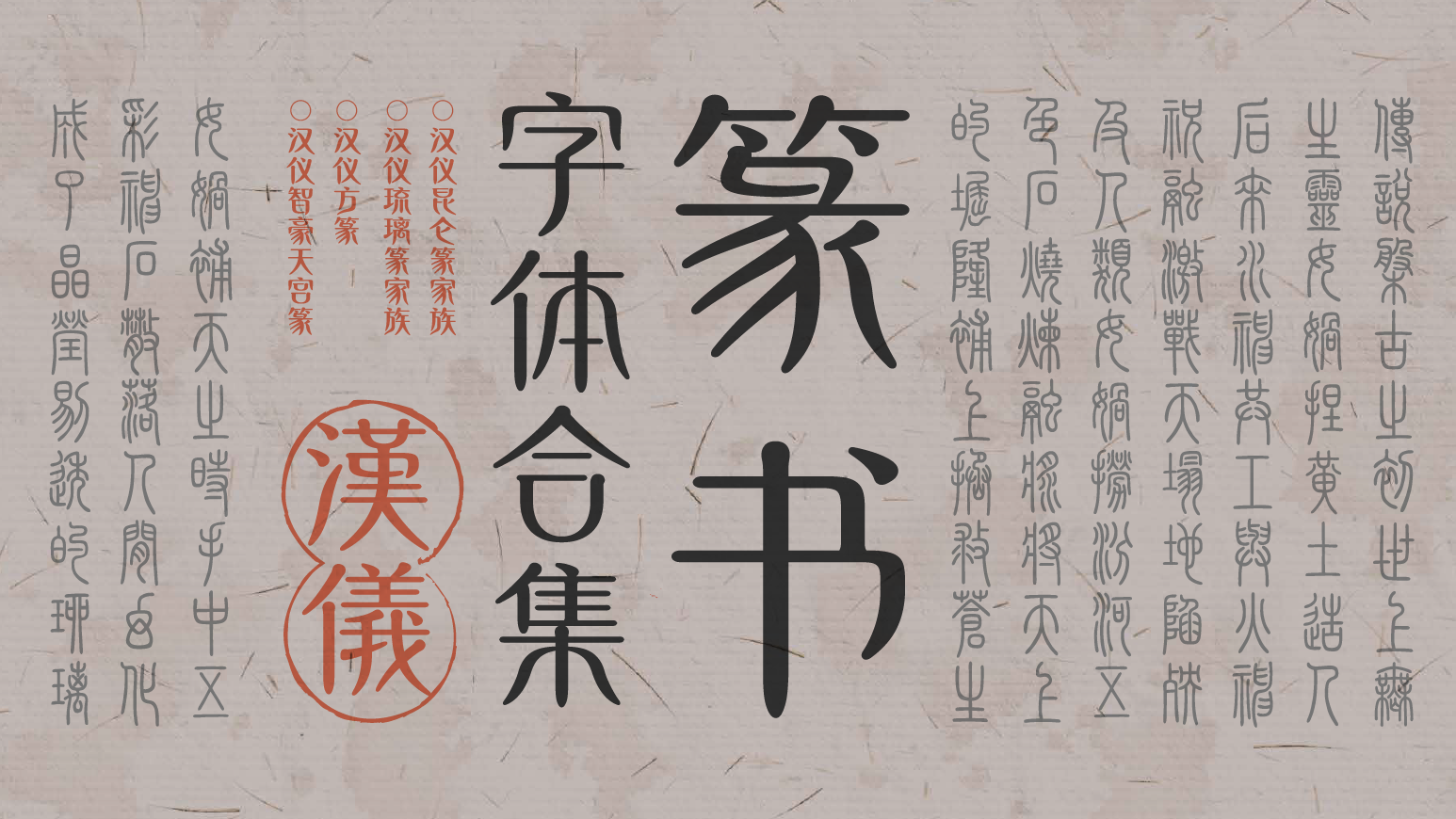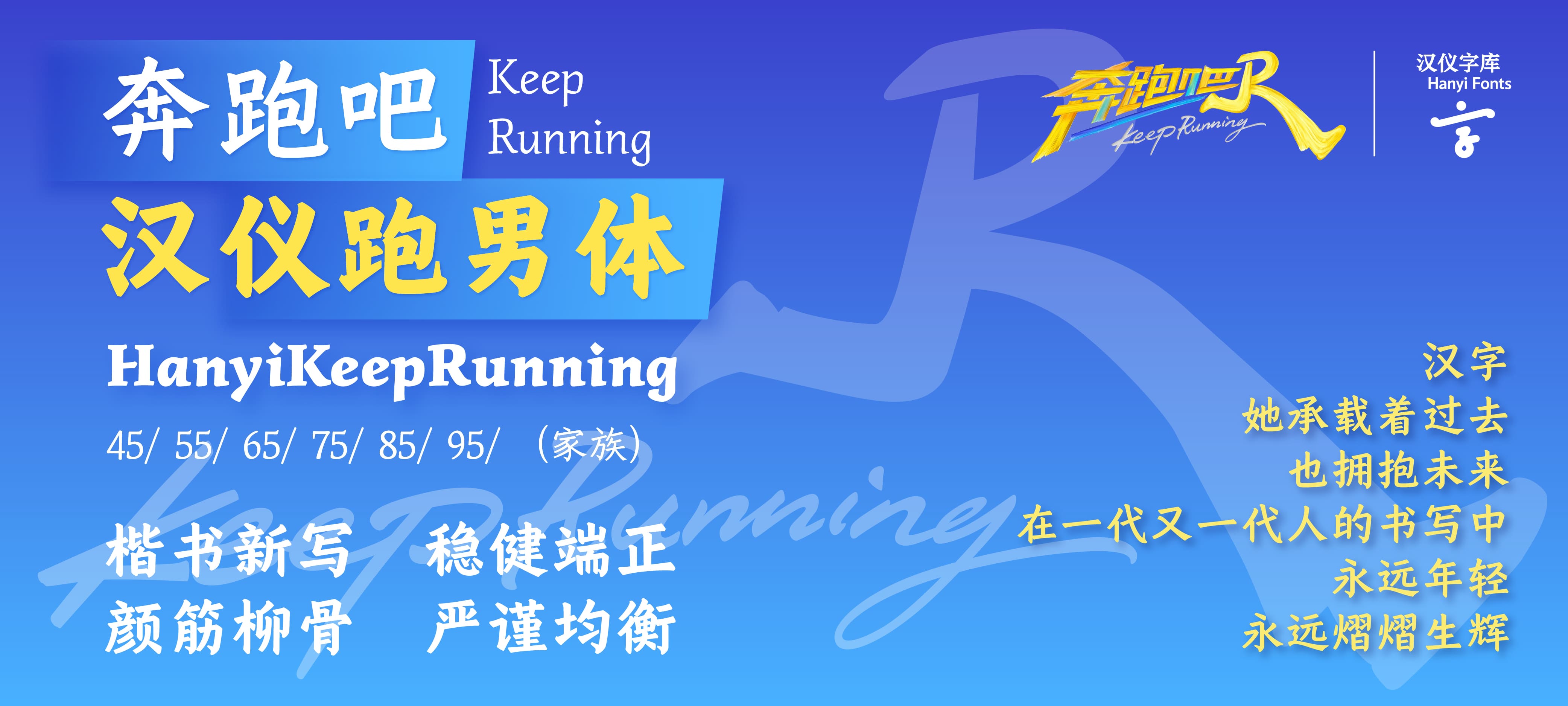
汉仪敦煌当代隶楷
HANYI DunHuangDangDaiLiKai
灵活随性,敦煌意趣
汉仪敦煌当代魏楷
HANYI DunHuangDangDaiWeiKai
修旧如旧,丝路遗韵
汉仪敦煌当代唐楷
HANYI DunHuangDangDaiTangKai
端庄静雅,大漠古韵
汉仪旗黑现代版
HANYI Qihei Geometric
现代风格几何感强烈,富有构成之美
汉仪旗黑人文版
HANYI Qihei Humanist
人文风格线条柔和,气韵自生
汉仪旗黑经典版
HANYI Qihei Grotesk
经典风格通用高效,简洁明快
汉仪上海滩
HANYI ShangHaiTan
温和克制,优雅舒展
汉仪昆仑篆
HANYI KunLunZhuan
从金石到雪域,从民族到世界
汉仪琉璃篆
HANYI LiuLiZhuan
流光溢彩,幻若琉璃
汉仪节奏黑
HANYI JieZouHei
斜体标语新趋势
汉仪国图创新山海经
HANYI GuoTuChuangXinShanHaiJing
古朴磅礴,刀刻俊朗
汉仪国图创新红楼梦
HANYI GuoTuChuangXinHongLouMeng
雍容气韵,俊逸风骨
汉仪跑男体
HANYI KeepRunning
颜筋柳骨,楷书新写
汉仪泡泡云蓝天版
HANYI PaoPaoYunSky
趣味膨胀,蓝天白云
汉仪风波莫吉托
HANYI FengBoMoJiTuo
连笔倾斜,有机流动